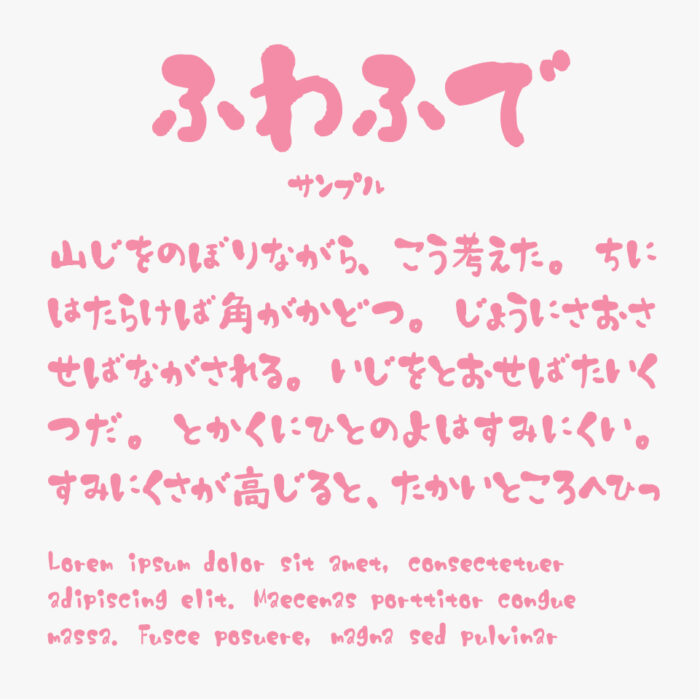
ふわふでフォントは、やわらかい筆で書いたような筆文字フォントです。
墨で書いたような滲み感や墨溜まりの質感ありとても渋い雰囲気がありますが、文字のフォルムがまるっとしていてふわふわな可愛いデザインになっています。
他のフォントにはない質感と可愛さを併せ持ったとってもキュートなフォントです。
収録文字は、第1水準漢字、ひらがな、カタカナ、アルファベット、数字が収録されています。